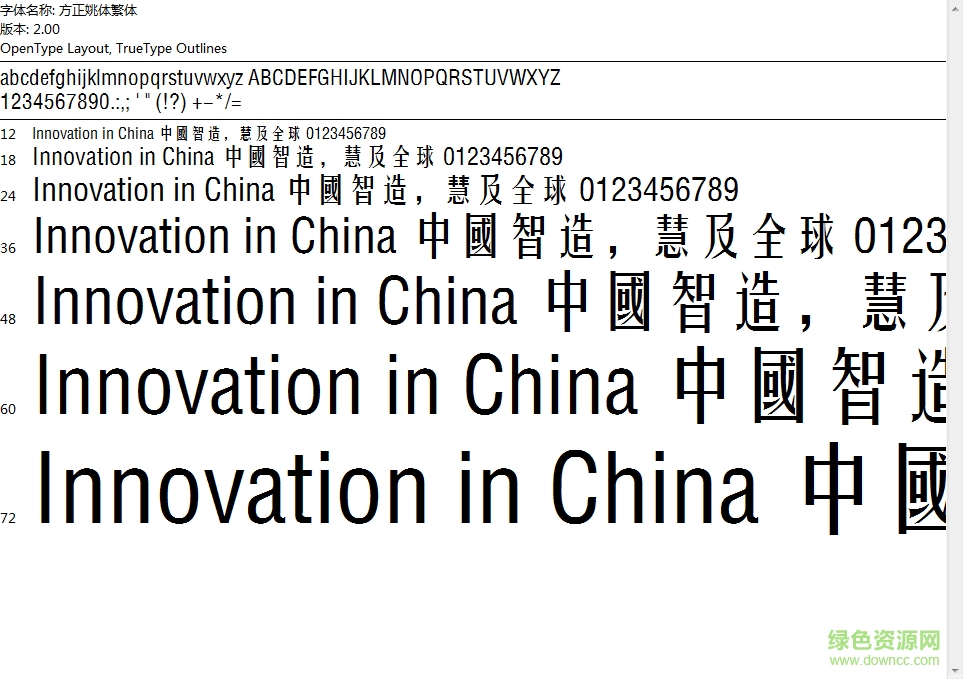
fzytfw字體就是方正姚體繁體字體,筆畫粗,字形瘦,規(guī)范工整。該字體適用領域十分廣泛,現(xiàn)綠色資源網(wǎng)提供fzytfwgb10字體下載,有需要的就來吧!姚體是原中華書局聚珍部主任姚志良于民國時期設計的。
“姚體”結(jié)合了黑體的剛勁、扁平和宋體的規(guī)整、簡潔,顯得粗壯、有力,迎合了“喊口號”的需求。
這款硬朗、清秀的字型一面世就好評如潮,至今仍經(jīng)久不衰。
《解放日報》高級技工姚志良在1957年篆刻整理的一種變體在文革期間被大量使用。